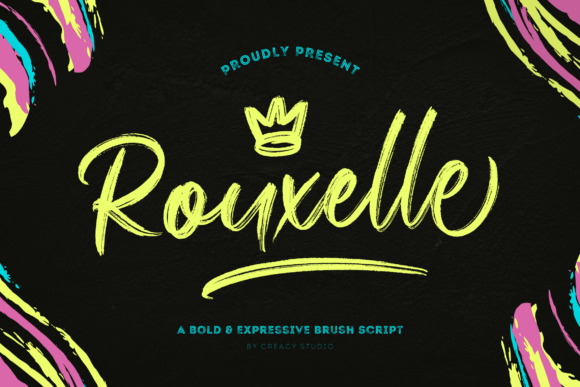
Rouxelle
Trouver les bons éléments de conception peut être un défi, mais Rouxelle propose une collection exceptionnelle qui rehausse instantanément votre travail.
Que vous créiez des produits POD (impression à la demande), des invitations de mariage ou des visuels pour les réseaux sociaux, Rouxelle est un choix idéal.